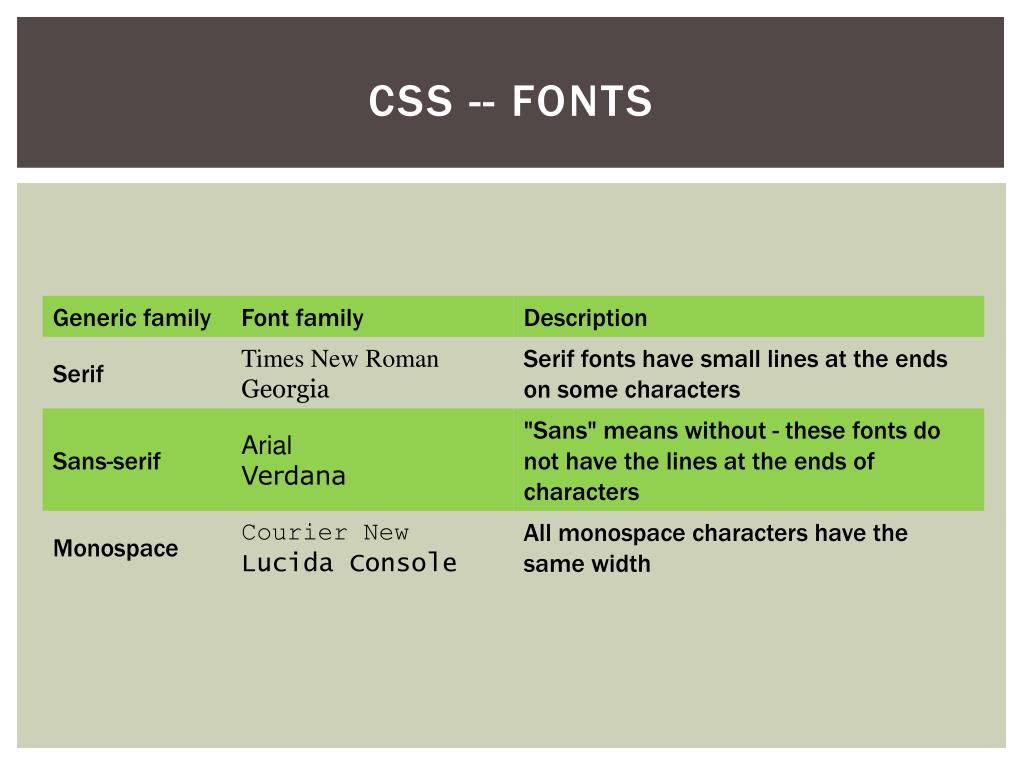
Безопасные шрифты на примере CSS
При создании сайтов, одним из основных элементов является используемый шрифт. Частенько вебмастера любят применять на сайте экзотические шрифты. Это конечно может смотреться круто, но нужно, чтобы данные шрифты были также установлены и у посетителя сайта, обычно на компьютерах у всех имеются лишь стандартные шрифты.
Поэтому, в данной статье мы рассмотрим основные шрифты, которые имеются практически на каждом компьютере. Также приведём примеры, как нужно размещать имена шрифтов, чтобы текст показался в любом случае, даже если данный шрифт отсутствует на компьютере пользователя.
Шрифты в языке CSS, назначаются элементам с помощью свойства font-family.
Список безопасных шрифтов (21 штука) и их примеры:
font-family: Arial, Helvetica, sans-serif; font-family: 'Arial Black', Gadget, sans-serif; font-family: 'Bookman Old Style', serif; font-family: 'Comic Sans MS', cursive; font-family: Courier, monospace; font-family: 'Courier New', Courier, monospace; font-family: Garamond, serif; font-family: Georgia, serif; font-family: Impact, Charcoal, sans-serif; font-family: 'Lucida Console', Monaco, monospace; font-family: 'Lucida Sans Unicode', 'Lucida Grande', sans-serif; font-family: 'MS Sans Serif', Geneva, sans-serif; font-family: 'MS Serif', 'New York', sans-serif; font-family: 'Palatino Linotype', 'Book Antiqua', Palatino, serif; font-family: Symbol, sans-serif; font-family: Tahoma, Geneva, sans-serif; font-family: 'Times New Roman', Times, serif; font-family: 'Trebuchet MS', Helvetica, sans-serif; font-family: Verdana, Geneva, sans-serif; font-family: Webdings, sans-serif; font-family: Wingdings, 'Zapf Dingbats', sans-serif;
Обратите внимание, что сначала идёт распространённый шрифт (например Arial), если его на компьютере посетителя нет, то идёт более распространённый и похожий на него (например Helvetica), и в конце если оба эти шрифта отсутствуют, подключается serif, sans-serif, monospace или cursive (данные способы начертания шрифта есть всегда).
Arial
Имя шрифта: font-family: Arial, Helvetica, sans-serif;
Цифры: 0 1 2 3 4 5 6 7 8 9
Arial Black
Имя шрифта: font-family: ‘Arial Black’, Gadget, sans-serif;
Bookman Old Style
Имя шрифта: font-family: ‘Bookman Old Style’, serif;
Цифры: 0 1 2 3 4 5 6 7 8 9
Comic Sans MS
Имя шрифта: font-family: ‘Comic Sans MS’, cursive;
Цифры: 0 1 2 3 4 5 6 7 8 9
Courier
Имя шрифта: font-family: Courier, monospace;
Цифры: 0 1 2 3 4 5 6 7 8 9
Courier New
Имя шрифта: font-family: ‘Courier New’, Courier, monospace;
Цифры: 0 1 2 3 4 5 6 7 8 9
Garamond
Имя шрифта: font-family: Garamond, serif;
Цифры: 0 1 2 3 4 5 6 7 8 9
Georgia
Имя шрифта: font-family: Georgia, serif;
Цифры: 0 1 2 3 4 5 6 7 8 9
Impact
Имя шрифта: font-family: Impact, Charcoal, sans-serif;
Цифры: 0 1 2 3 4 5 6 7 8 9
Lucida Console
Имя шрифта: font-family: ‘Lucida Console’, Monaco, monospace;
Цифры: 0 1 2 3 4 5 6 7 8 9
Lucida Sans Unicode
Имя шрифта: font-family: ‘Lucida Sans Unicode’, ‘Lucida Grande’, sans-serif;
Цифры: 0 1 2 3 4 5 6 7 8 9
MS Sans Serif
Имя шрифта: font-family: ‘MS Sans Serif’, Geneva, sans-serif;
Цифры: 0 1 2 3 4 5 6 7 8 9
MS Serif
Имя шрифта: font-family: ‘MS Serif’, ‘New York’, sans-serif;
Цифры: 0 1 2 3 4 5 6 7 8 9
Palatino Linotype
Имя шрифта: font-family: ‘Palatino Linotype’, ‘Book Antiqua’, Palatino, serif;
Symbol
Имя шрифта: font-family: Symbol, sans-serif;
Цифры: 0 1 2 3 4 5 6 7 8 9
Tahoma
Имя шрифта: font-family: Tahoma, Geneva, sans-serif;
Цифры: 0 1 2 3 4 5 6 7 8 9
Times New Roman
Имя шрифта: font-family: ‘Times New Roman’, Times, serif;
Цифры: 0 1 2 3 4 5 6 7 8 9
Trebuchet MS
Имя шрифта: font-family: ‘Trebuchet MS’, Helvetica, sans-serif;
Цифры: 0 1 2 3 4 5 6 7 8 9
Verdana
Имя шрифта: font-family: Verdana, Geneva, sans-serif;
Цифры: 0 1 2 3 4 5 6 7 8 9
Webdings
Имя шрифта: font-family: Webdings, sans-serif;
Цифры: 0 1 2 3 4 5 6 7 8 9
Wingdings
Цифры: 0 1 2 3 4 5 6 7 8 9
5) Веб Безопасные HTML & CSS Шрифты
Что такое веб-безопасный шрифт?
Чтобы шрифт был читаемым, а также выглядел одинаково в любом браузере или устройстве (например, на мобильном устройстве и в Интернете), шрифт должен быть установлен на этом устройстве.
Шрифты Web Safe обычно предварительно устанавливаются на большинство компьютеров, мобильных телефонов и планшетов устройства.
1) Ариал
Arial FontArial — это популярные шрифты без засечек. Он наиболее подходит для оконного устройства и используется вместо неподдерживаемых шрифтов.
2) Курьер Новый
Курьер Новый ШрифтCourier new — это устаревший газетный шрифт HTML-стиля. Это правильный выбор для вас, если вы ищете простой моноширинный шрифт.
3) Times New Roman
Times New Roman ШрифтЭто самый популярный шрифт на устройстве Windows — лучший выбор для любого профессионального сайта.
4) Грузия
Georgia FontGeorgia — это настоящий веб-шрифт с простой линией san serif и большим верхним размером. Письмо почти вытянуто, что облегчает чтение онлайн-шрифта.
5) Воздействие
Ударный шрифт6) Comic Sans MS
Comic Sans MS FontComic Sans MS — это шрифт для несерьезного письма. В основном он используется для передачи анекдотов, несерьезных литературных материалов.
Этот каллиграфический шрифт, созданный по почерку дизайнера Ричарда Брэдли, ассоциируется с непринужденной индивидуальностью. Он идеально подходит для использования в заголовках, декоративном тексте и коротких текстах.
16. Brush Script MT (курсив)
Brush Script MT — сильно украшенный скриптовый шрифт, имитирующий быстрые рукописные штрихи.Хотя у некоторых читателей он может вызвать ностальгию, лучше всего ограничить использование этого шрифта декоративными элементами, поскольку его стиль достигается за счет удобочитаемости.
17. Луминари (фантазия)